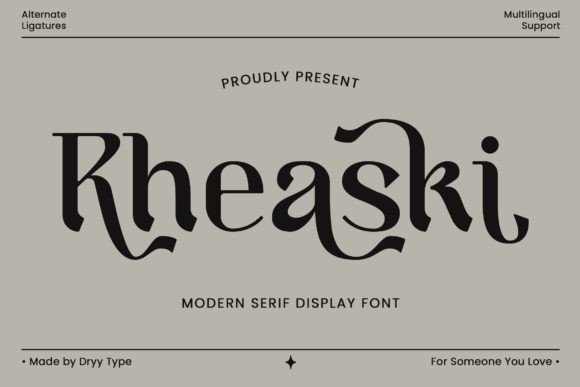
Rheaski
หากคุณกำลังมองหาเนื้อหาคุณภาพสูงเช่น Rheaski แพ็คเกจพรีเมียมนี้เป็นตัวเลือกที่ยอดเยี่ยมสำหรับโปรเจ็กต์สร้างสรรค์ของคุณ
ไม่ว่าคุณจะสร้างผลิตภัณฑ์ POD (Print on Demand) คำเชิญงานแต่งงาน หรือกราฟิกโซเชียลมีเดีย Rheaski ก็เหมาะสมอย่างยิ่ง